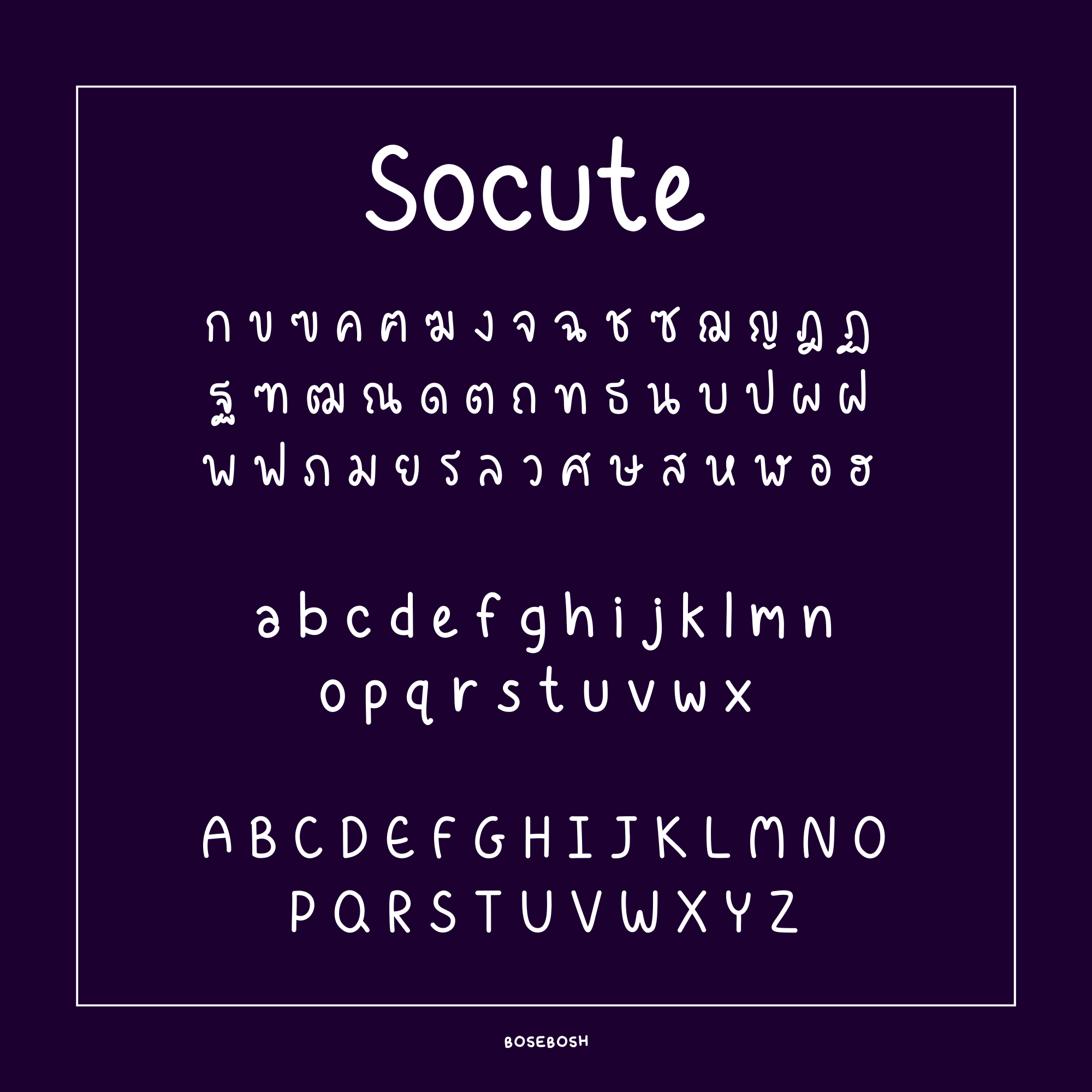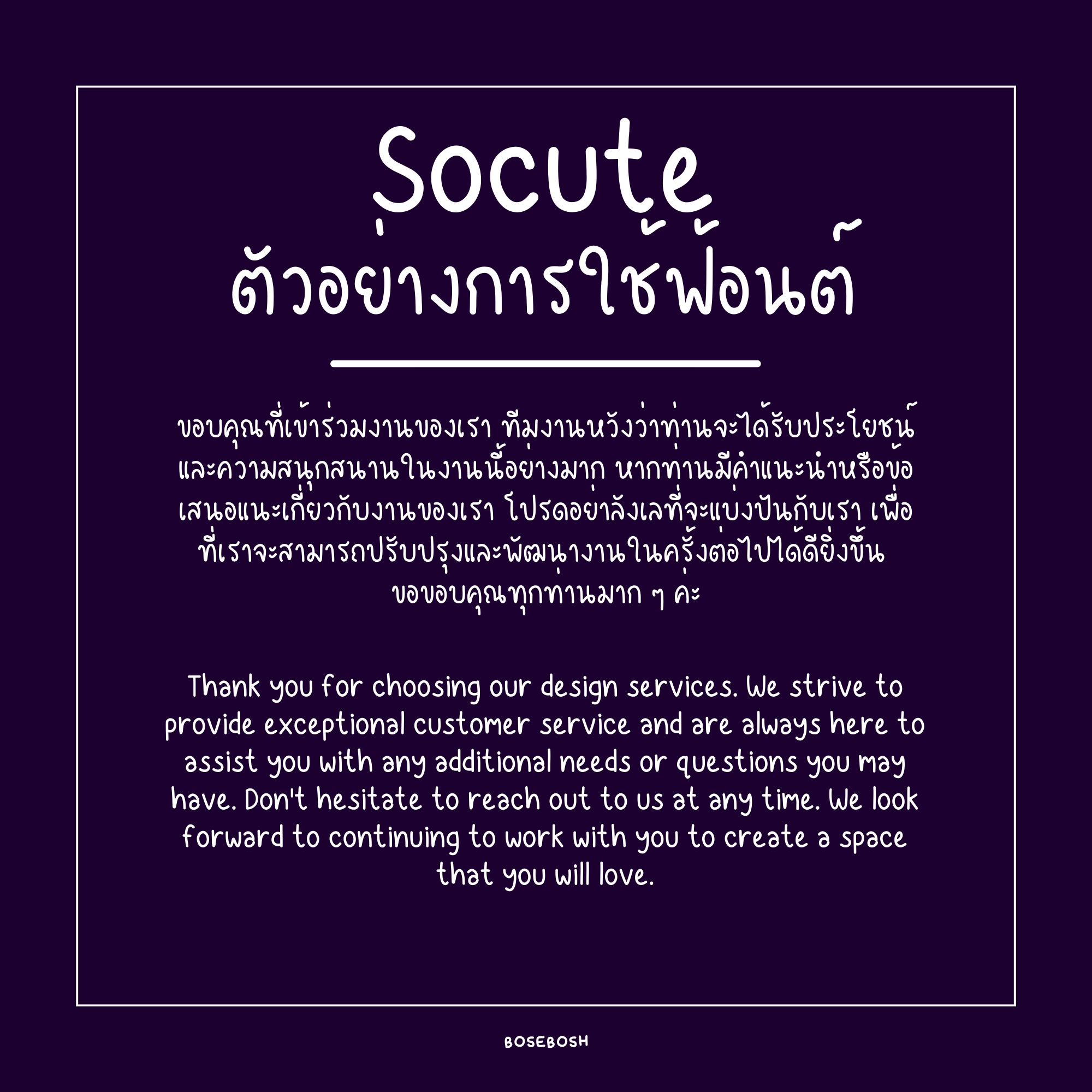
Socute Font
✏️ Socute — ฟอนต์ลายมือน่ารักพิเศษ เส้นบางแต่ชัดเจน ให้ฟีลแบบน่ารักจริงใจ
🎯 ตัวอักษรเรียงเส้นกลมกลืนดี รองรับทั้งไทย อังกฤษ และตัวเลขครบ
💡 เหมาะสำหรับทำป้ายคำพูด, โปสเตอร์ให้กำลังใจ, หรือข้อความประกอบภาพแนวอบอุ่น
🖋️ ถูกออกแบบให้เหมือนลายมือจริง อ่านง่าย สบายตา
🔠 รองรับทั้งภาษาไทย ภาษาอังกฤษ ตัวเลขอารบิก และเลขไทย